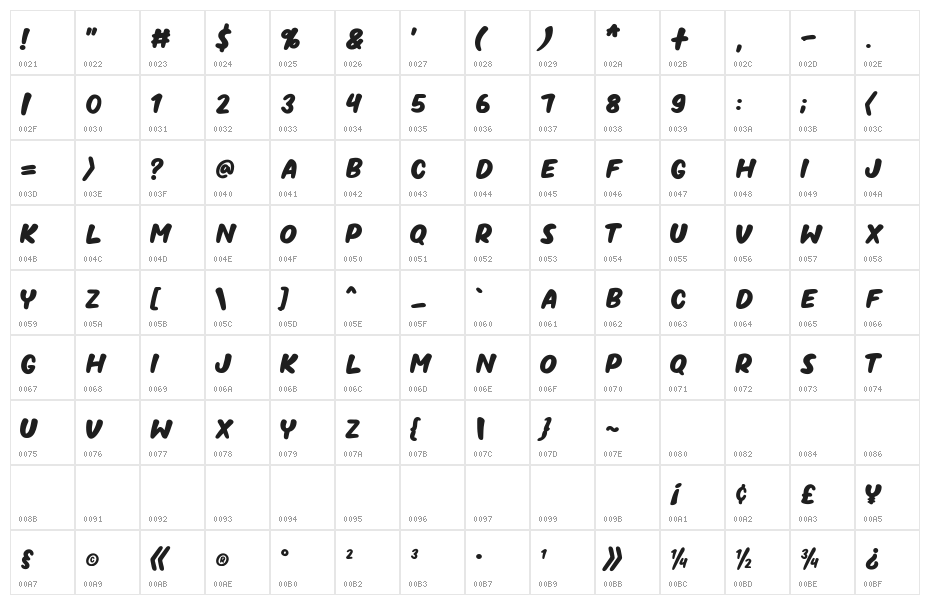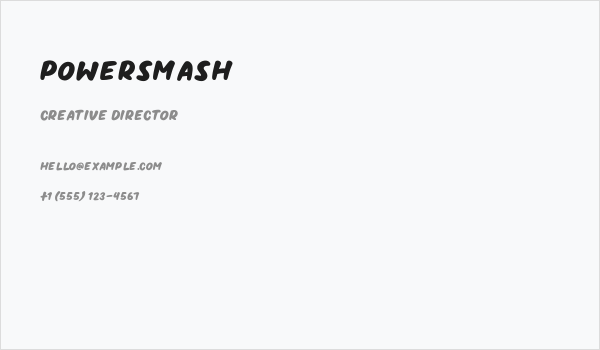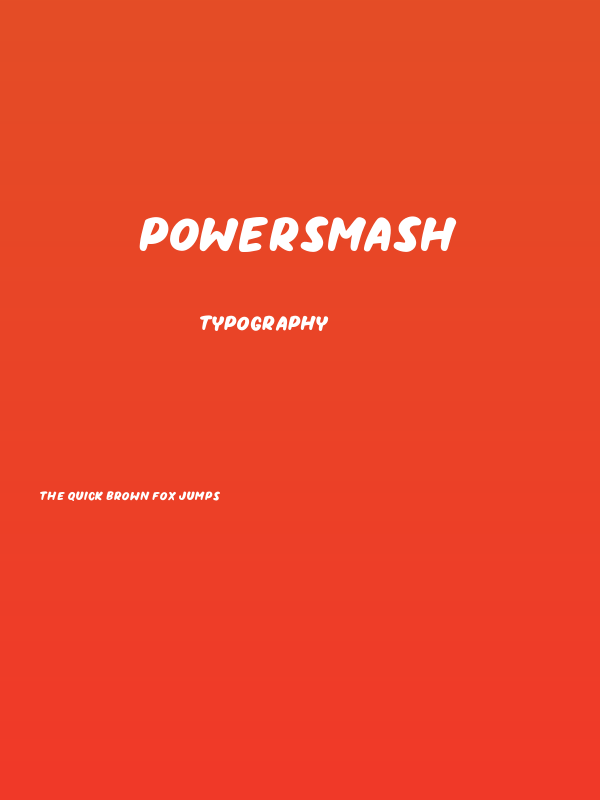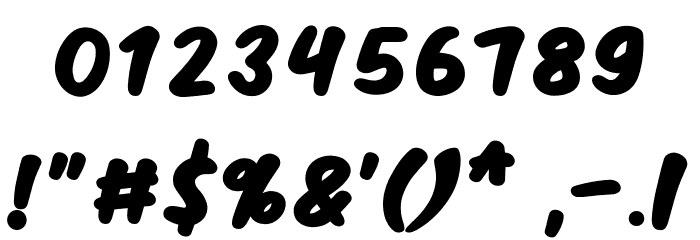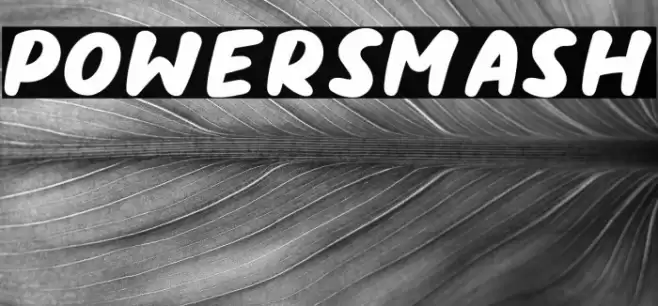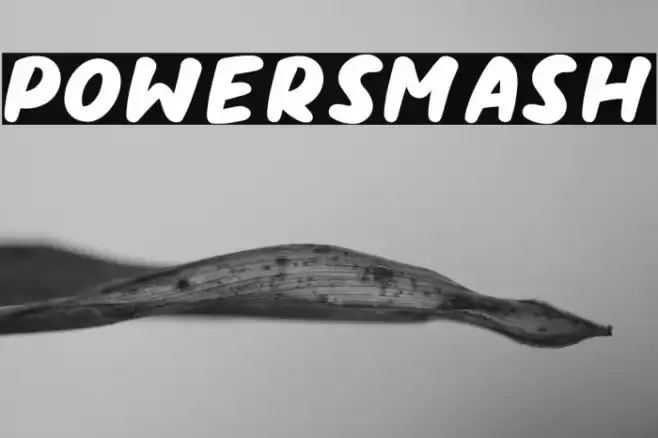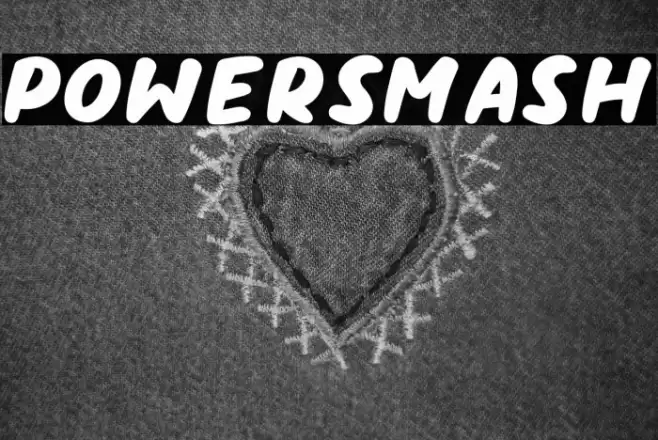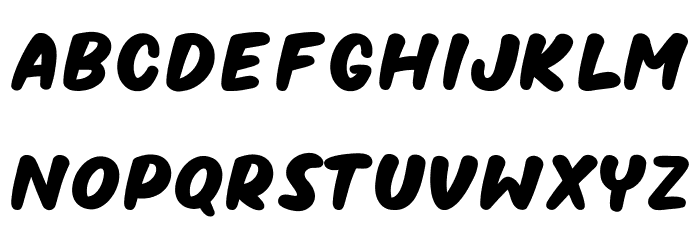
PowerSmash Font
| Gesamtstil | Playful |
| Anwendungsfall | Logos, Headlines, Posters |
| Vorgeschlagene Projekte | Ideal for children's books, playful branding, casual invitations, and social media graphics. |